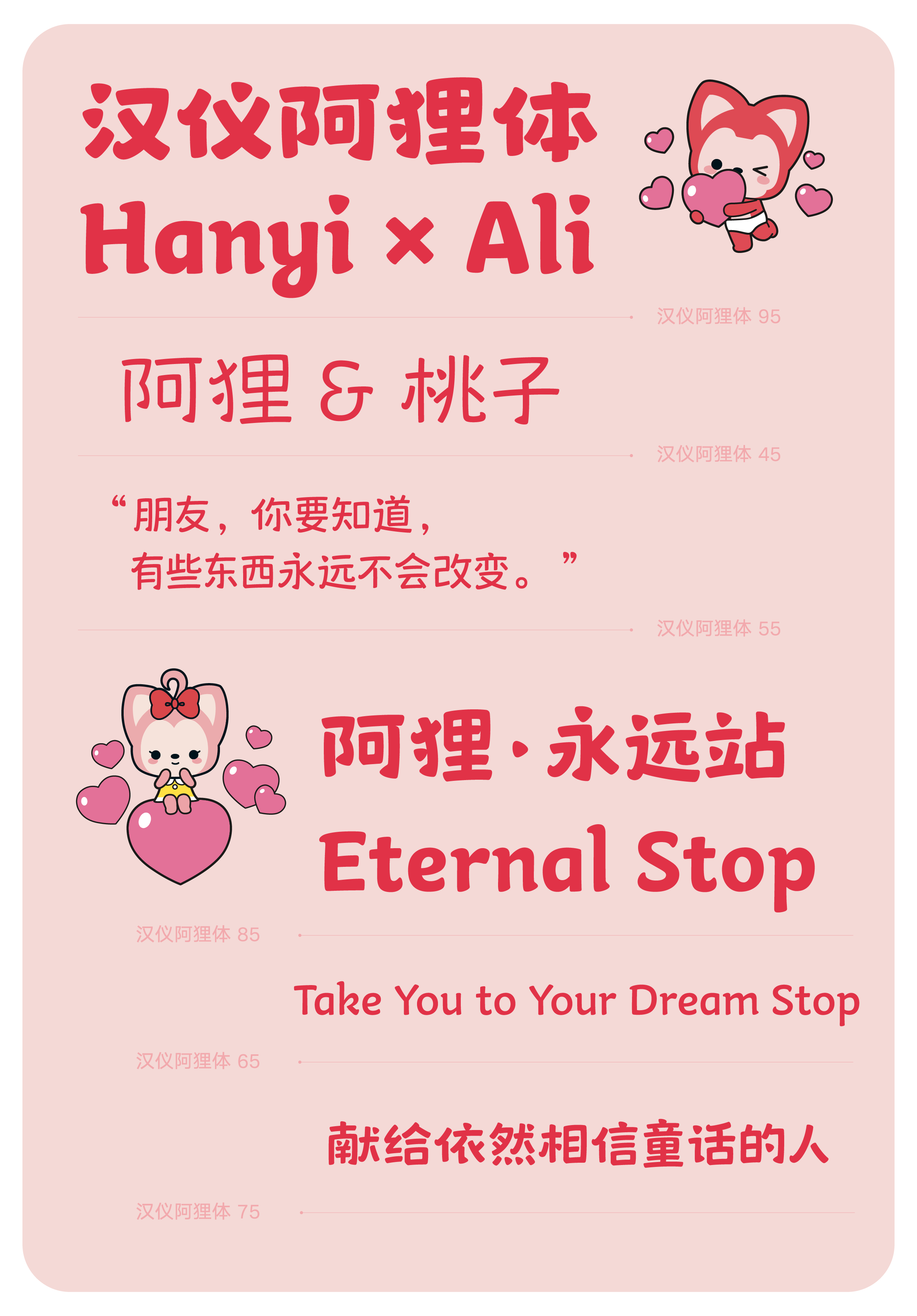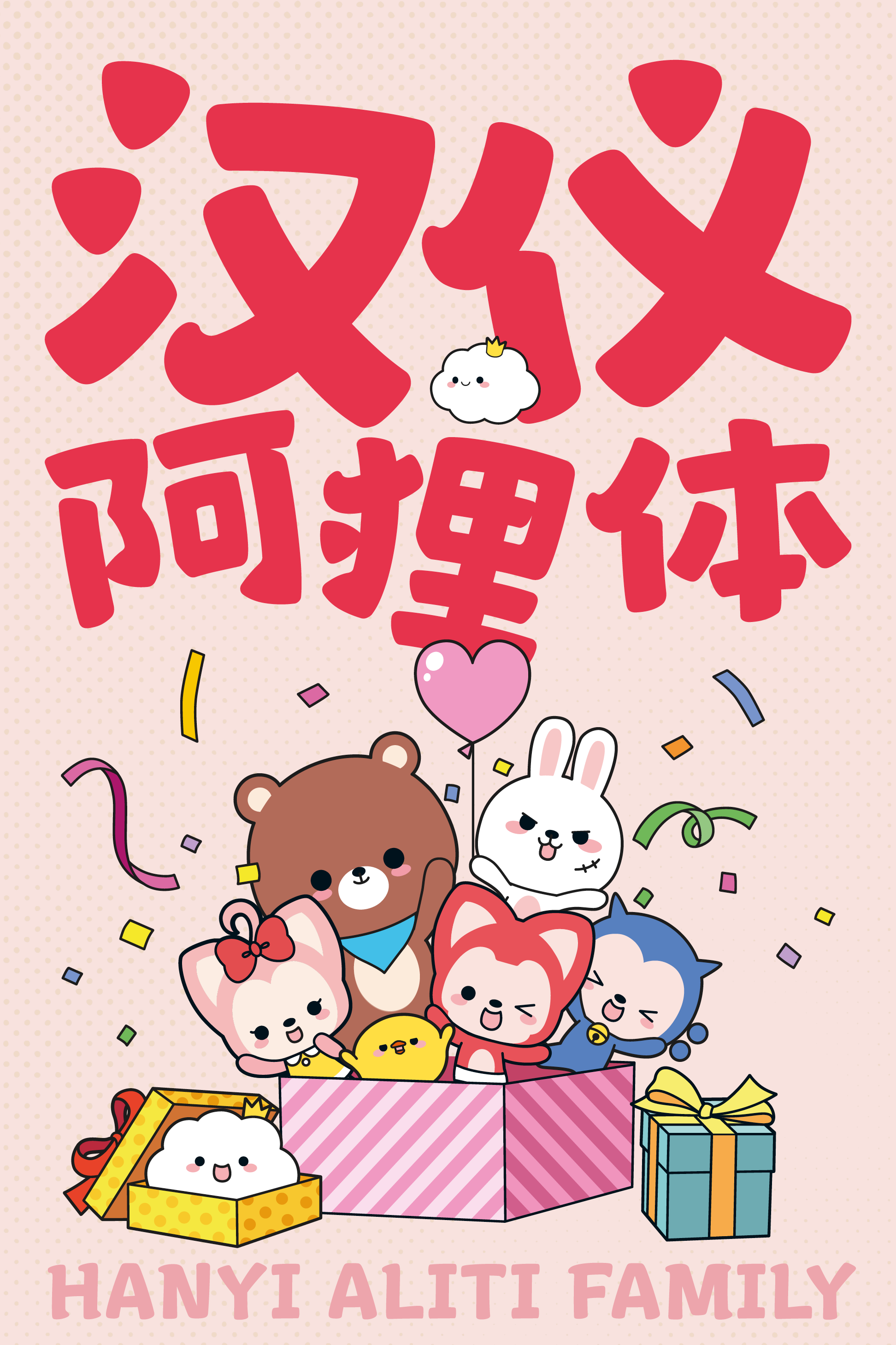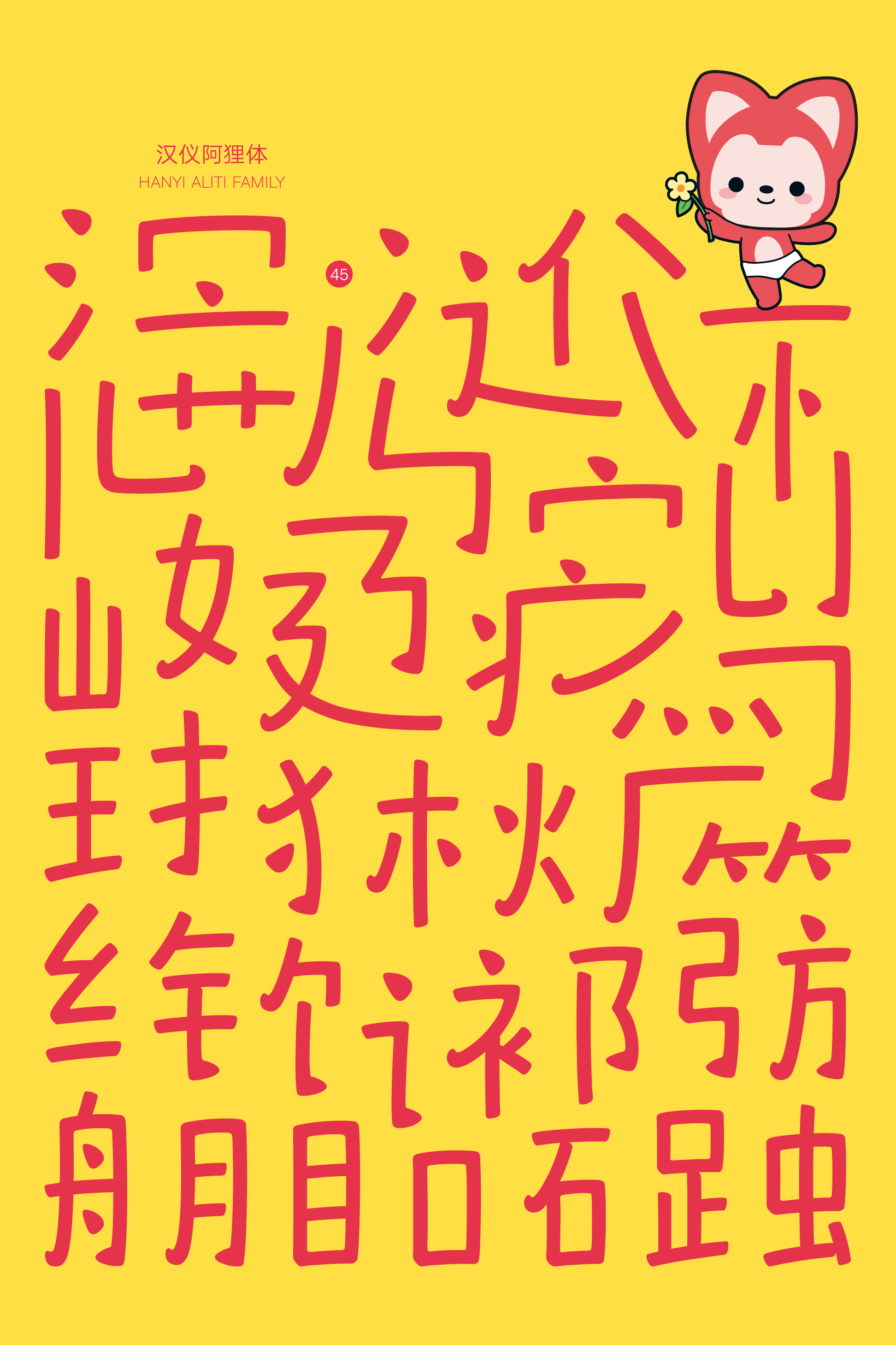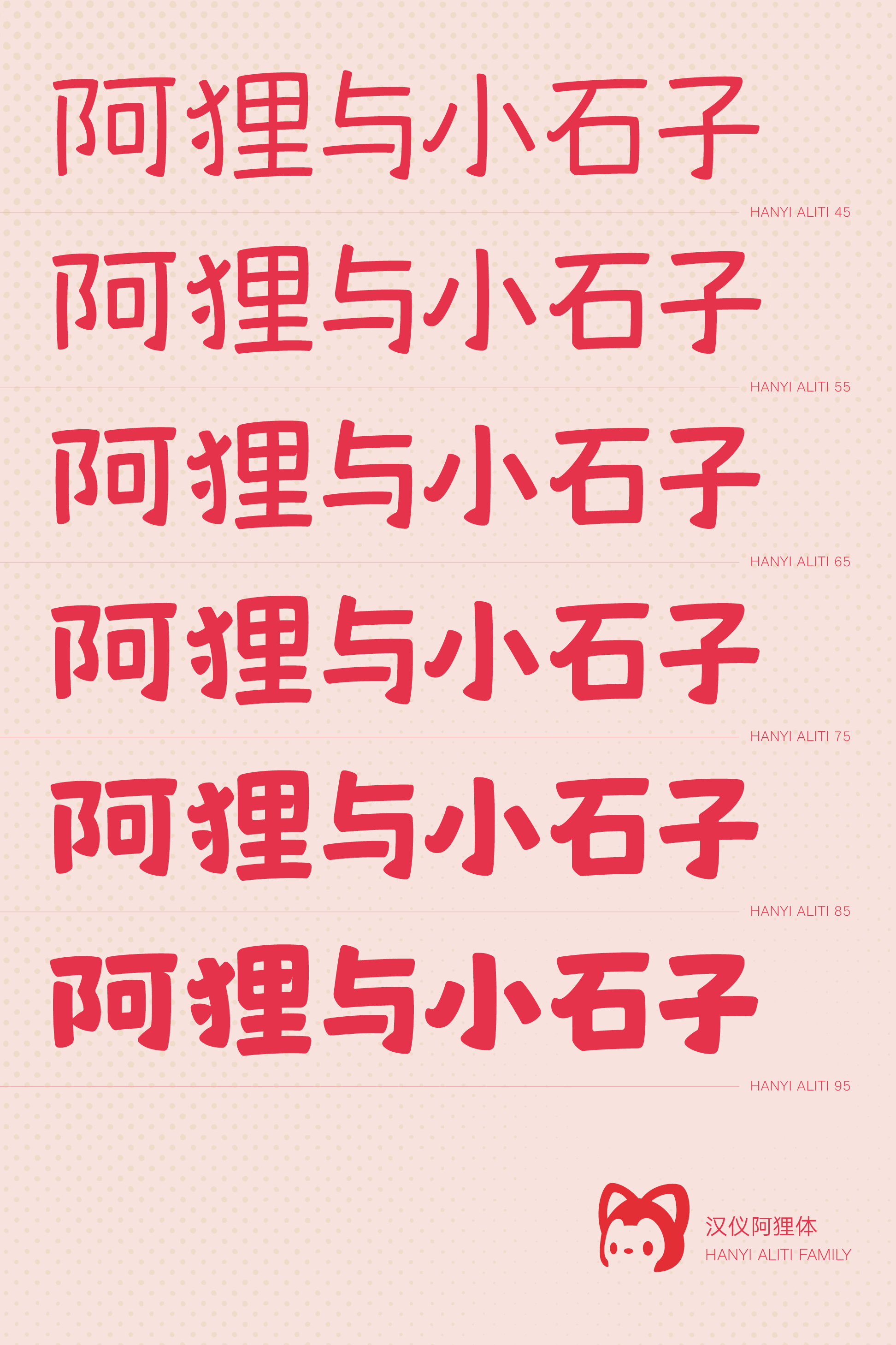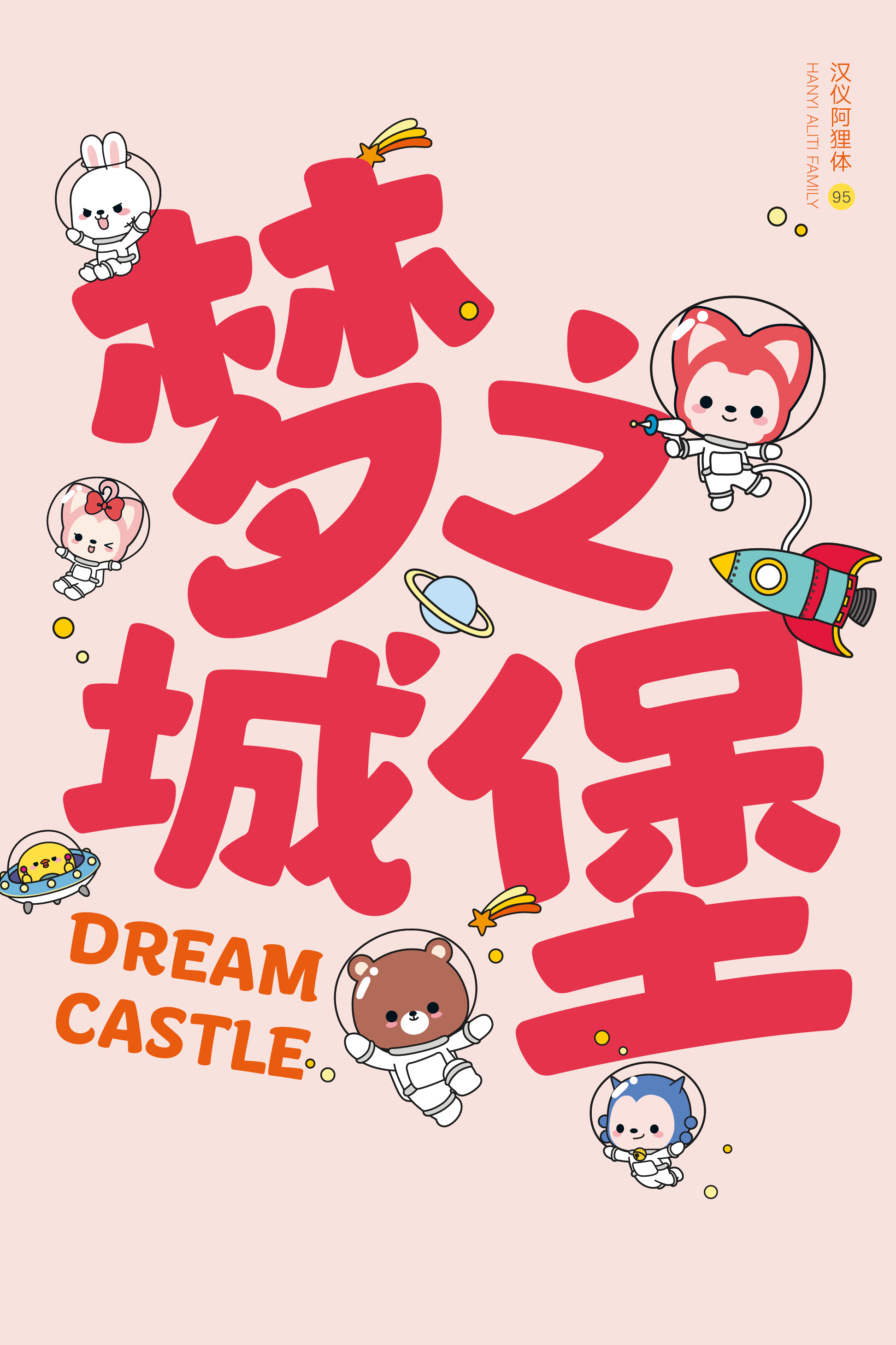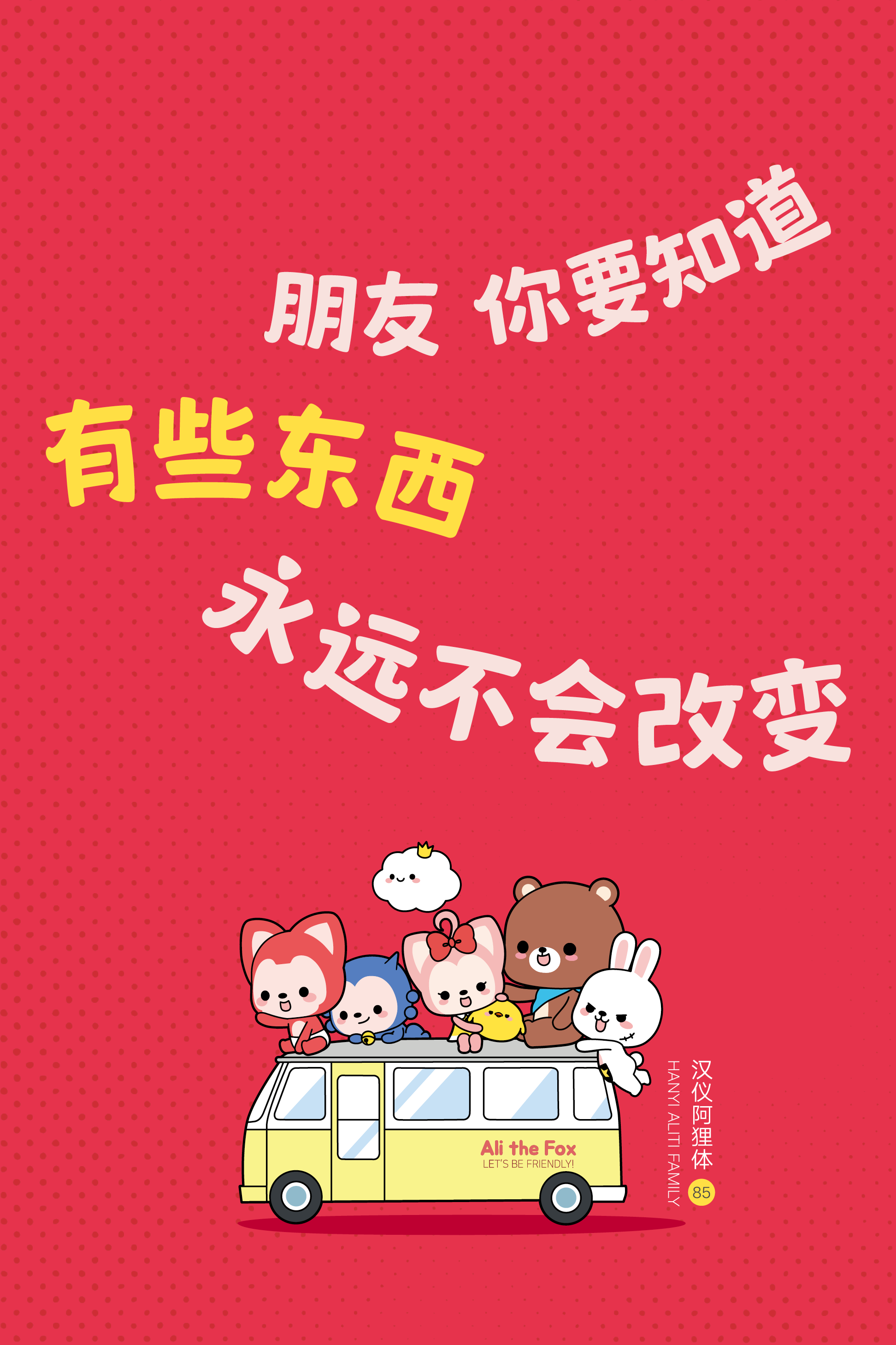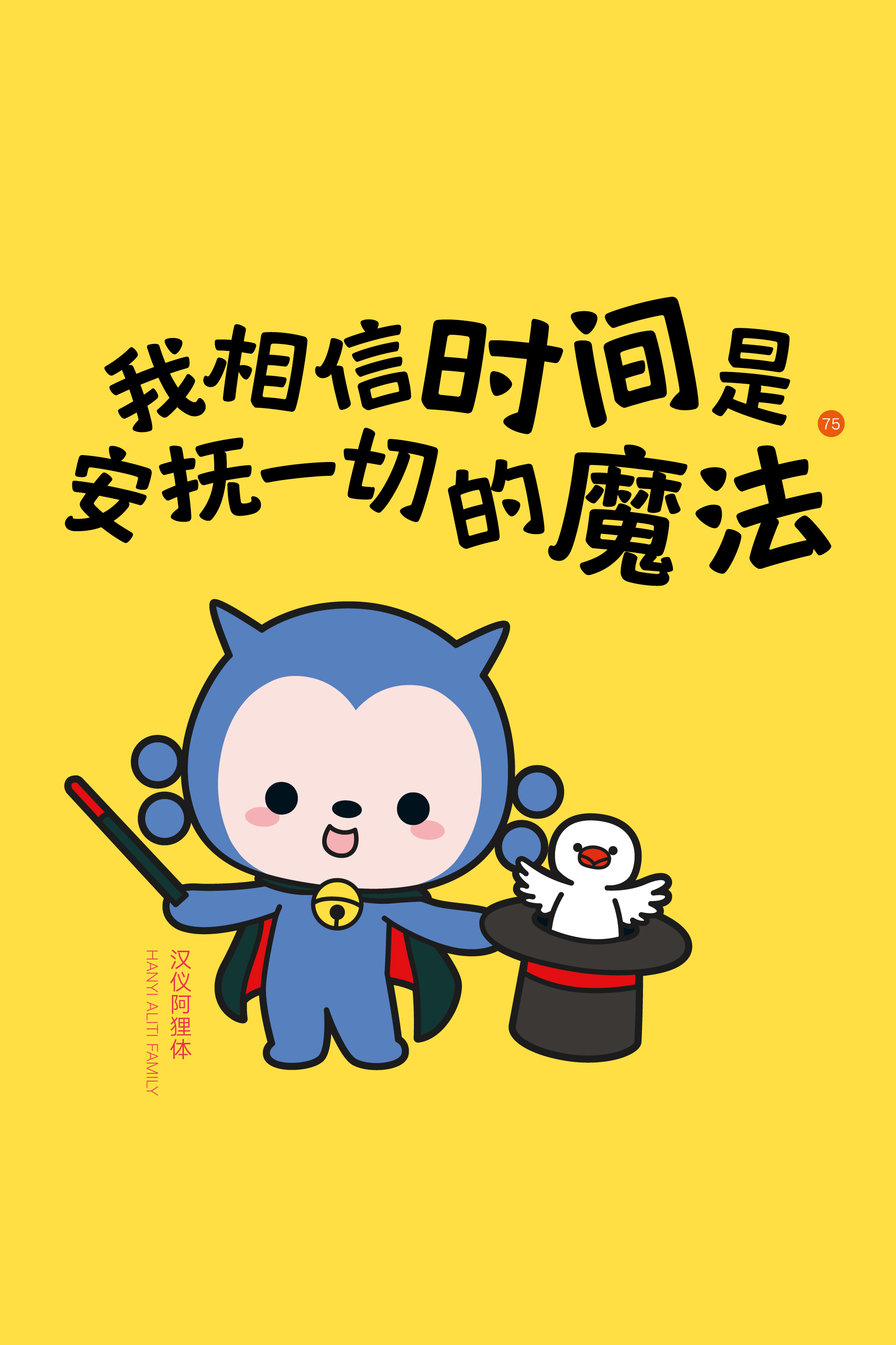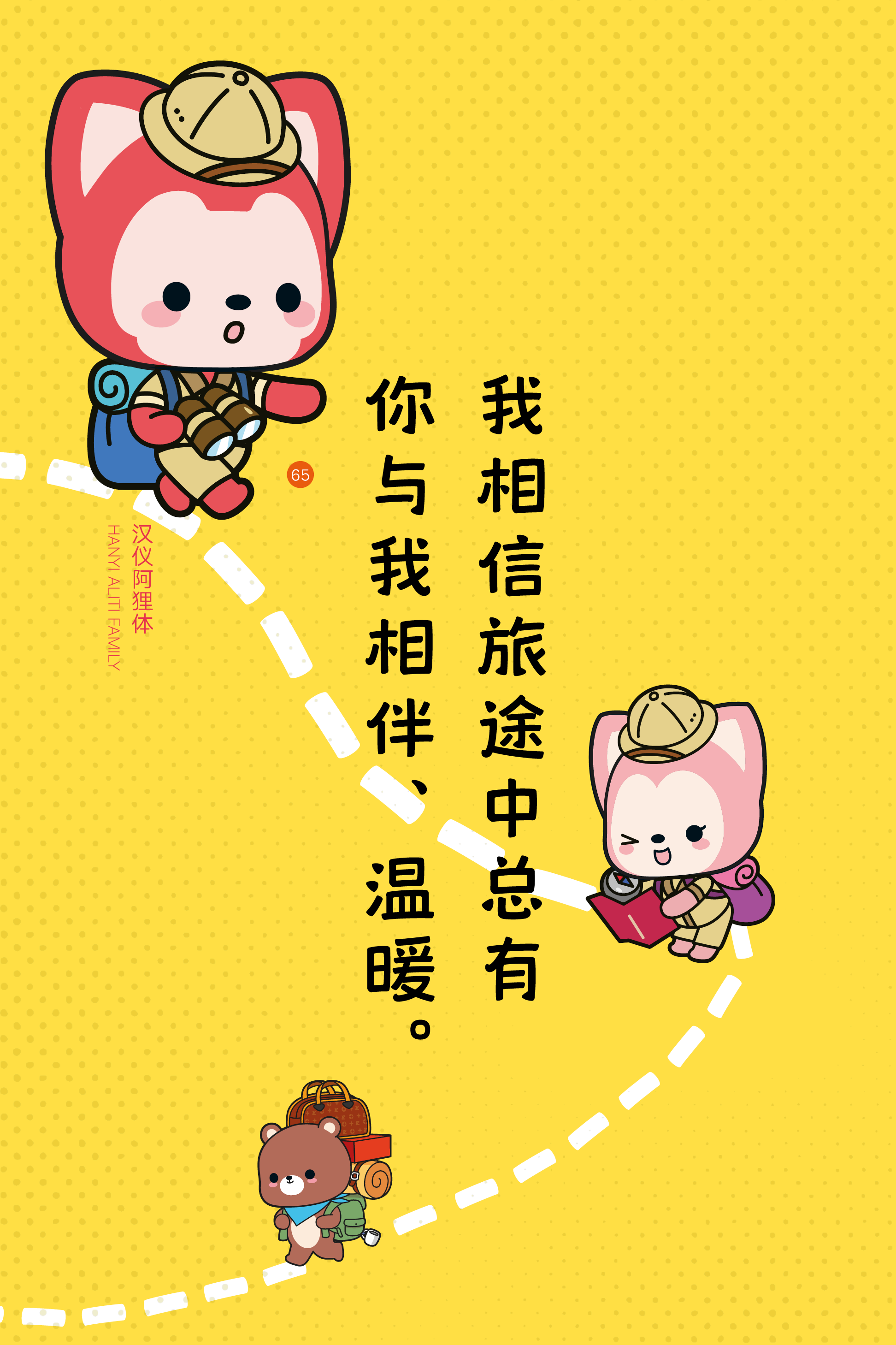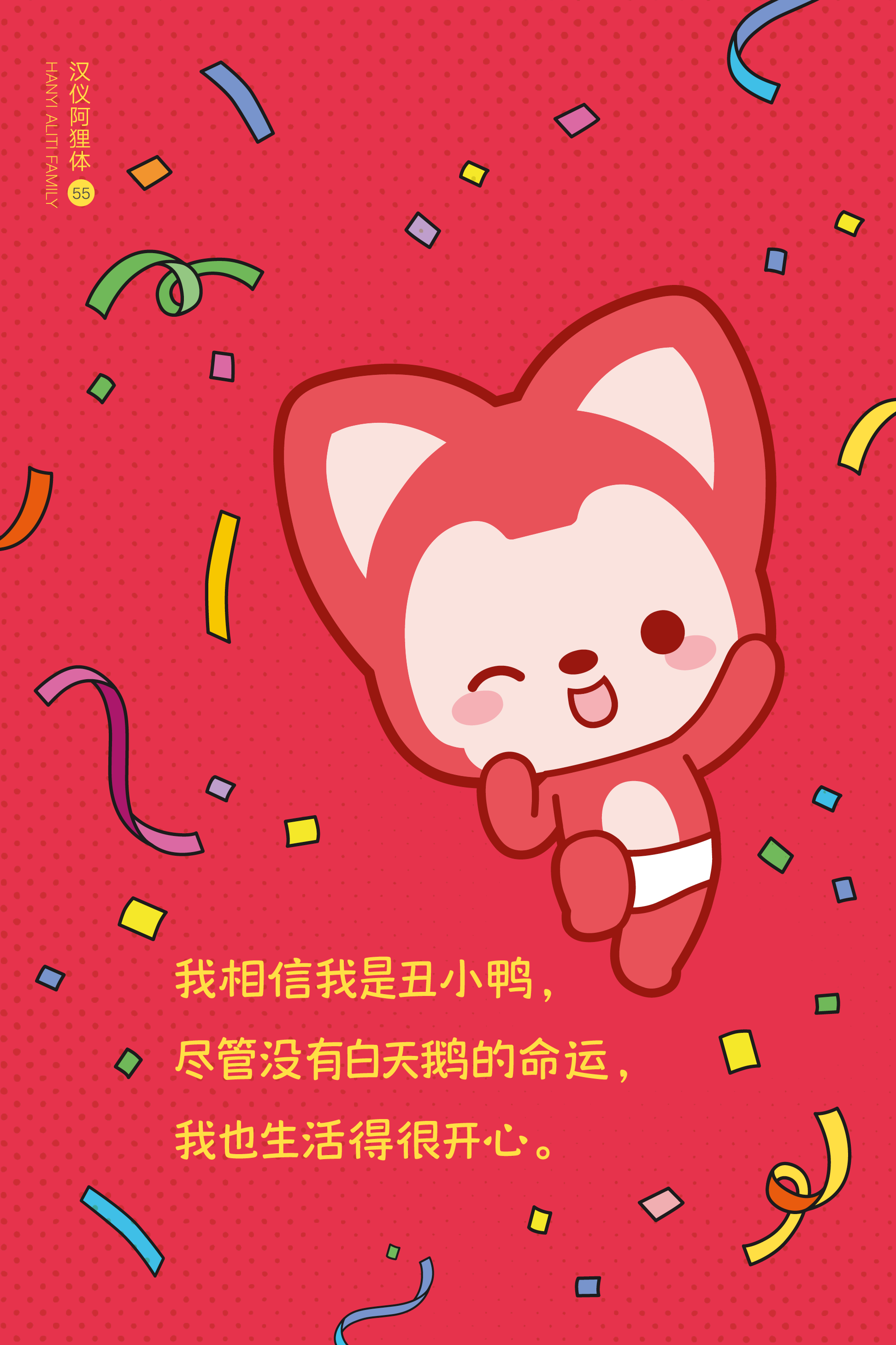
一直相信童画的阿狸来啦!
你,还相信童话吗?
阿狸与汉仪字库合作推出「汉仪阿狸体」,献给依然相信童话的人,希望这套家族字体可以带你重温最初的美好,陪你一起向着永远站前进。
阿狸的耳朵、桃子的呆毛,这些细节都藏在字体里面啦:
以阿狸标志性的大耳朵作为笔画的起点,三角造型的耳朵是这款字体的主要视觉元素。
桃子的呆毛也出现在笔画中,俏皮可爱。
笔画有弹性,整体有膨胀感,充满孩子气。
横笔向右上倾斜,带有跳跃的动态。
乖巧方整的字面依不同字形而略有大小变化,呈现活泼的节奏。
同一字形内,放大部件之间的比例关系。
由于字面大小富于微妙变化,采取了细致的变宽处理,使排版效果自然舒适,提升阅读体验。
西文部分延续了以阿狸耳朵造型为起点的笔画设计。
轴线略微向左倾斜,增添活泼的韵律感。
起笔衬线的造型是桃子的呆毛,整体细节更加丰富。
「汉仪阿狸体」家族包含由粗至细共6种字重,从标题到正文都放心地交给阿狸吧!